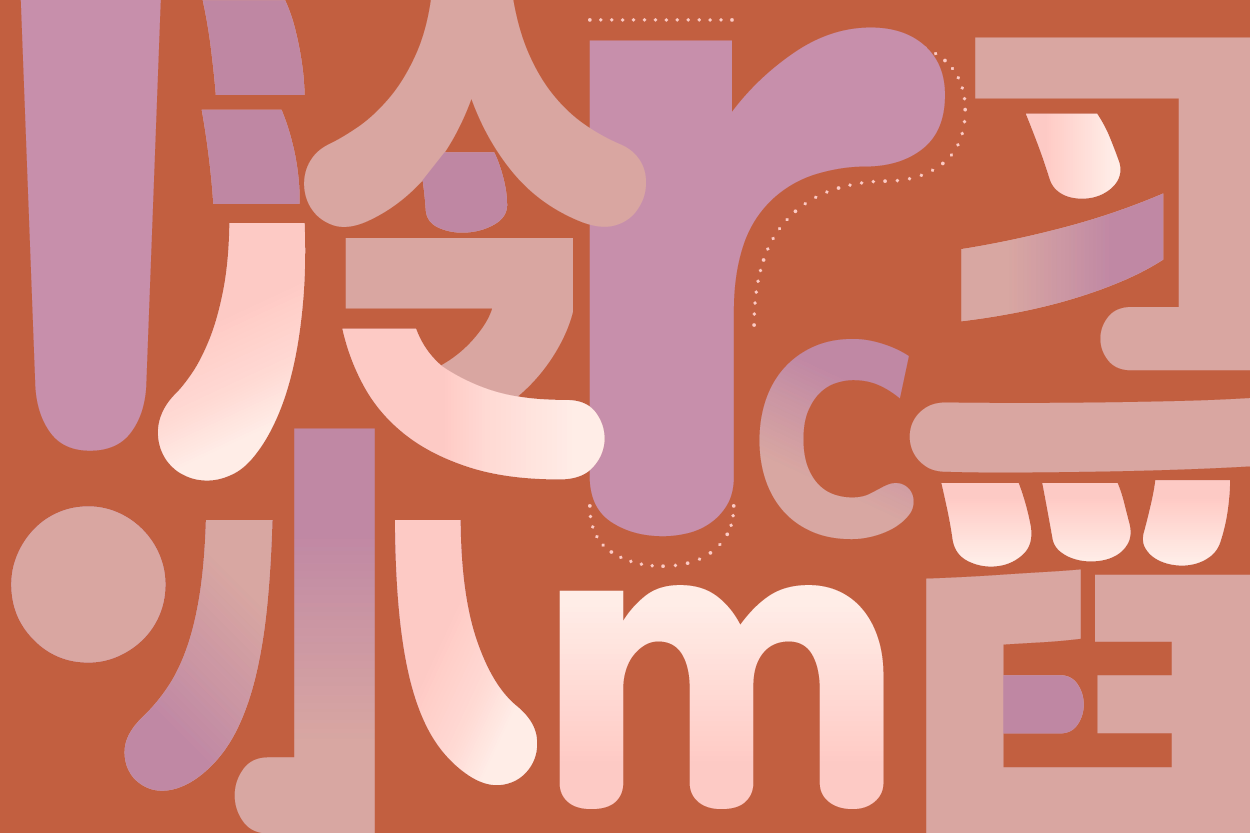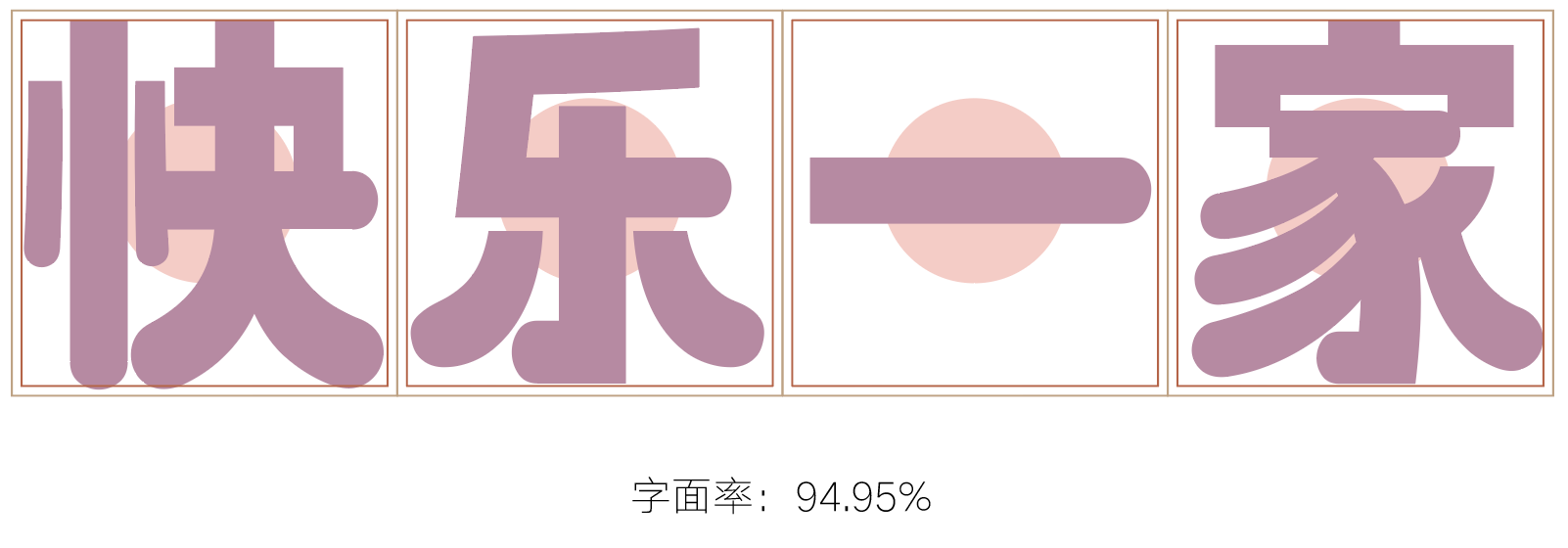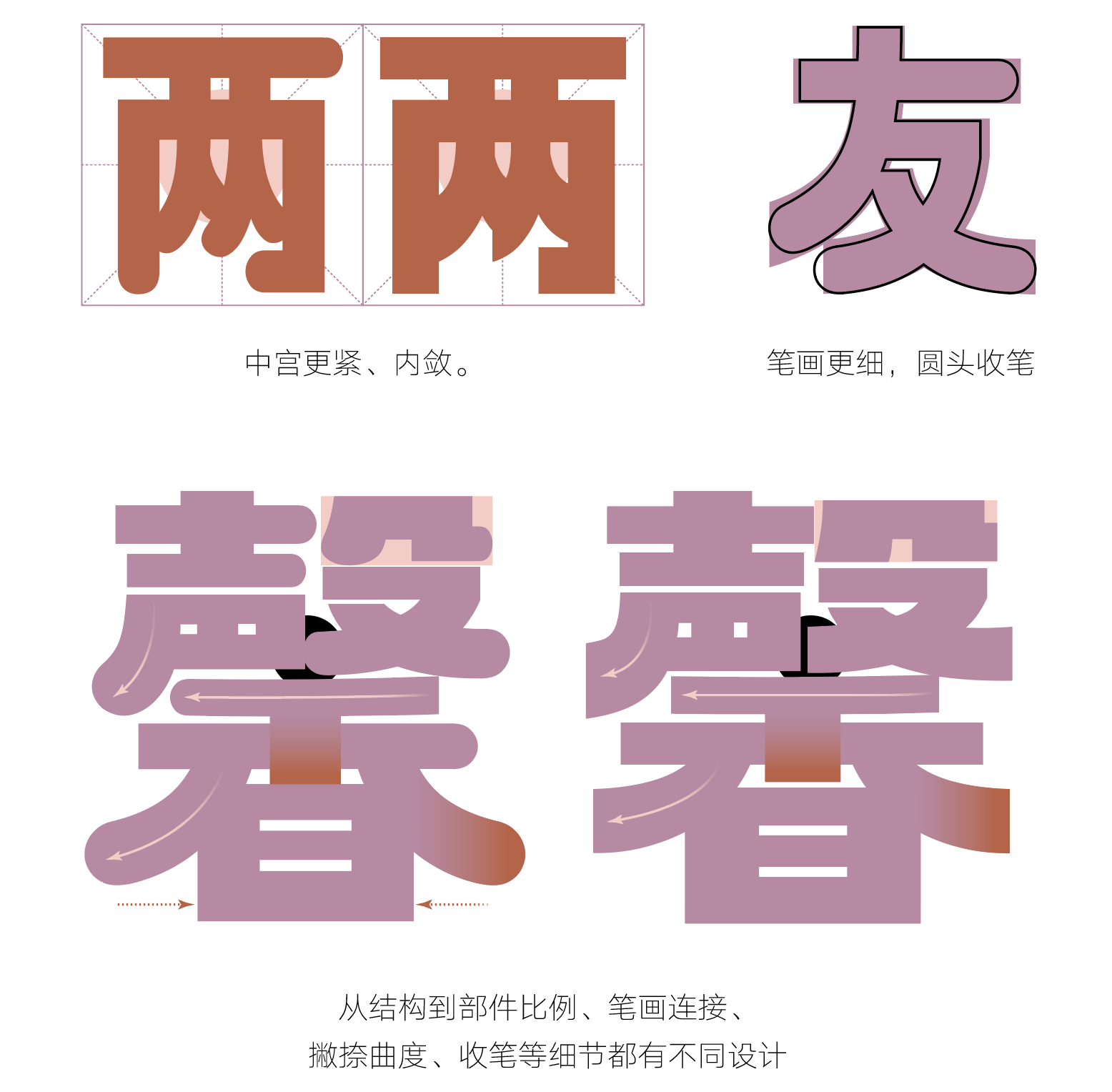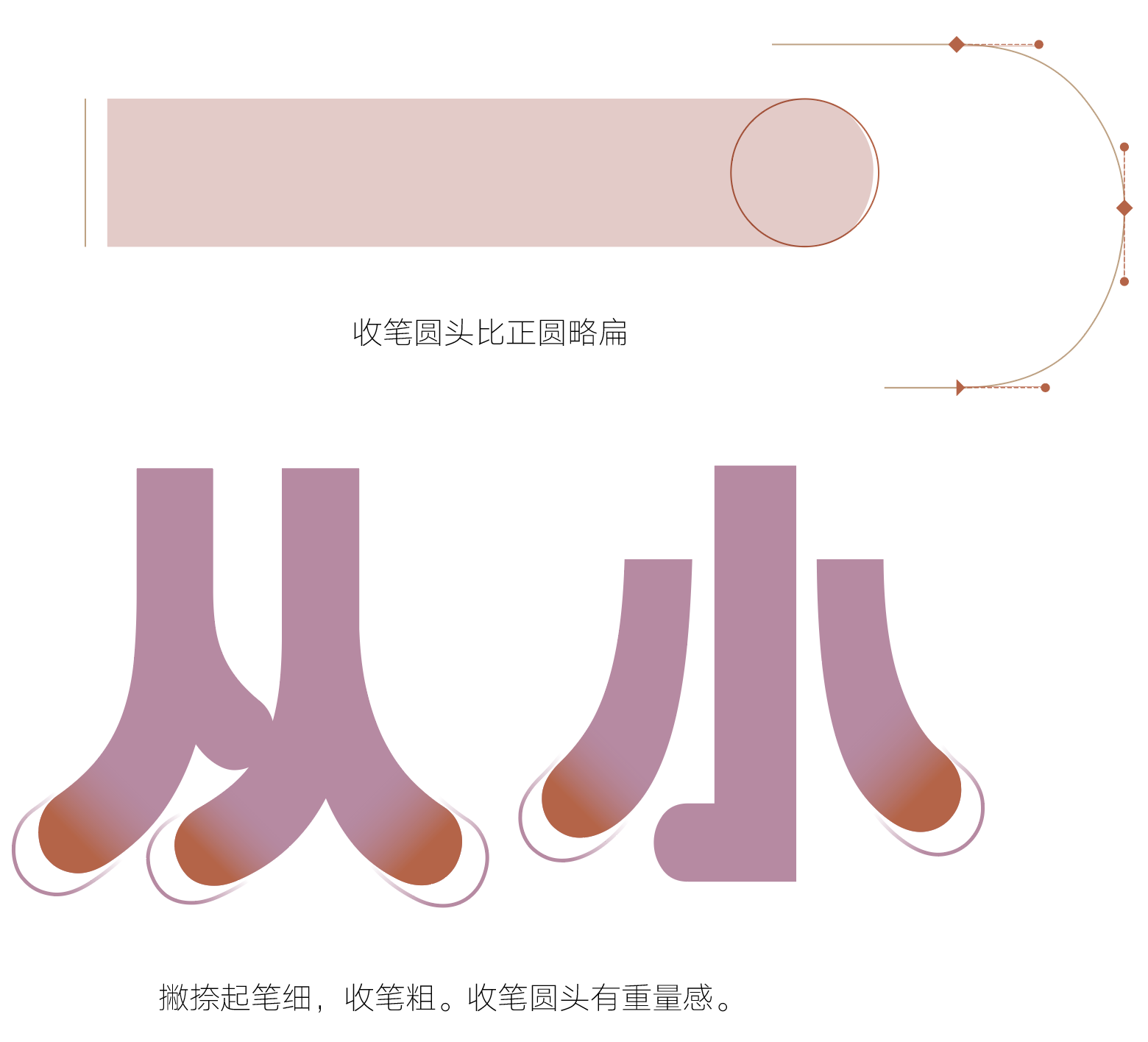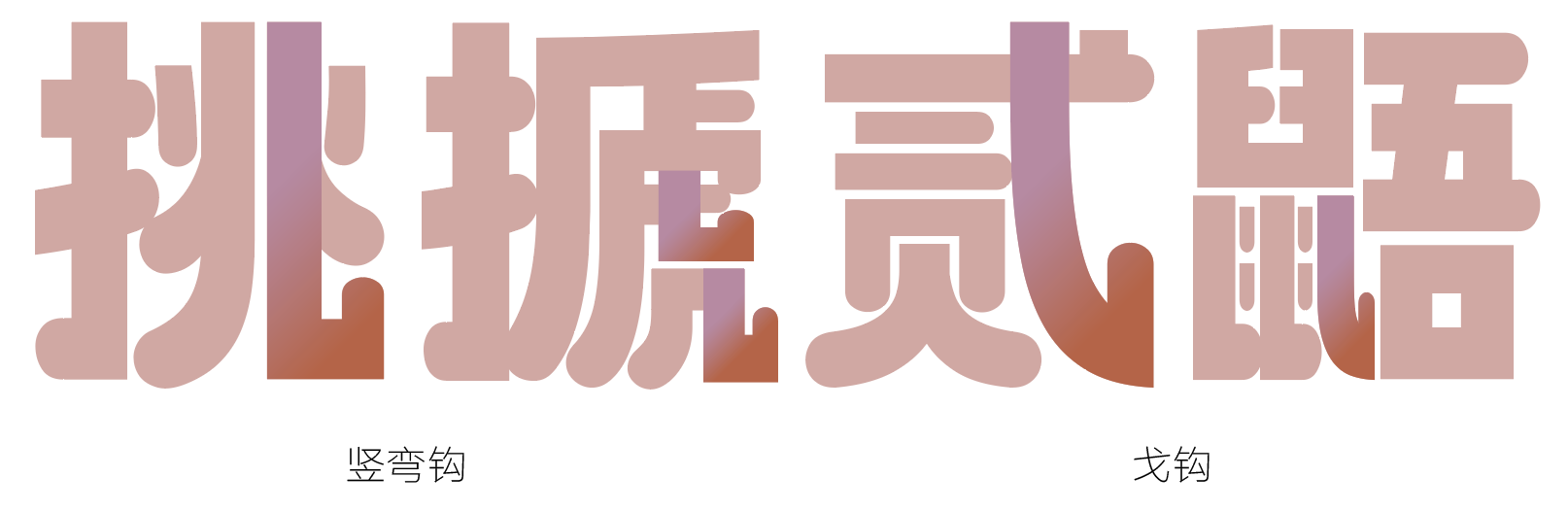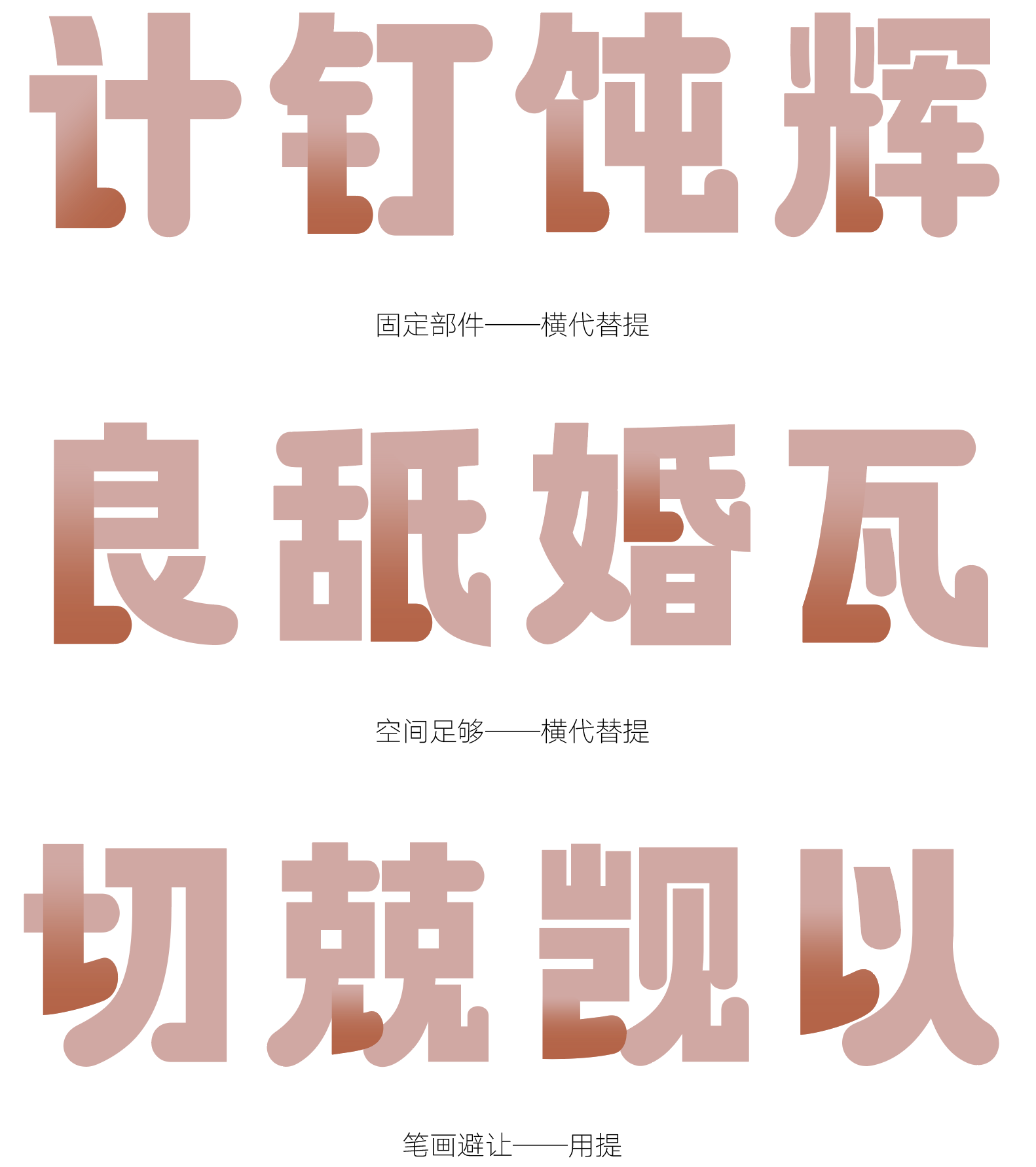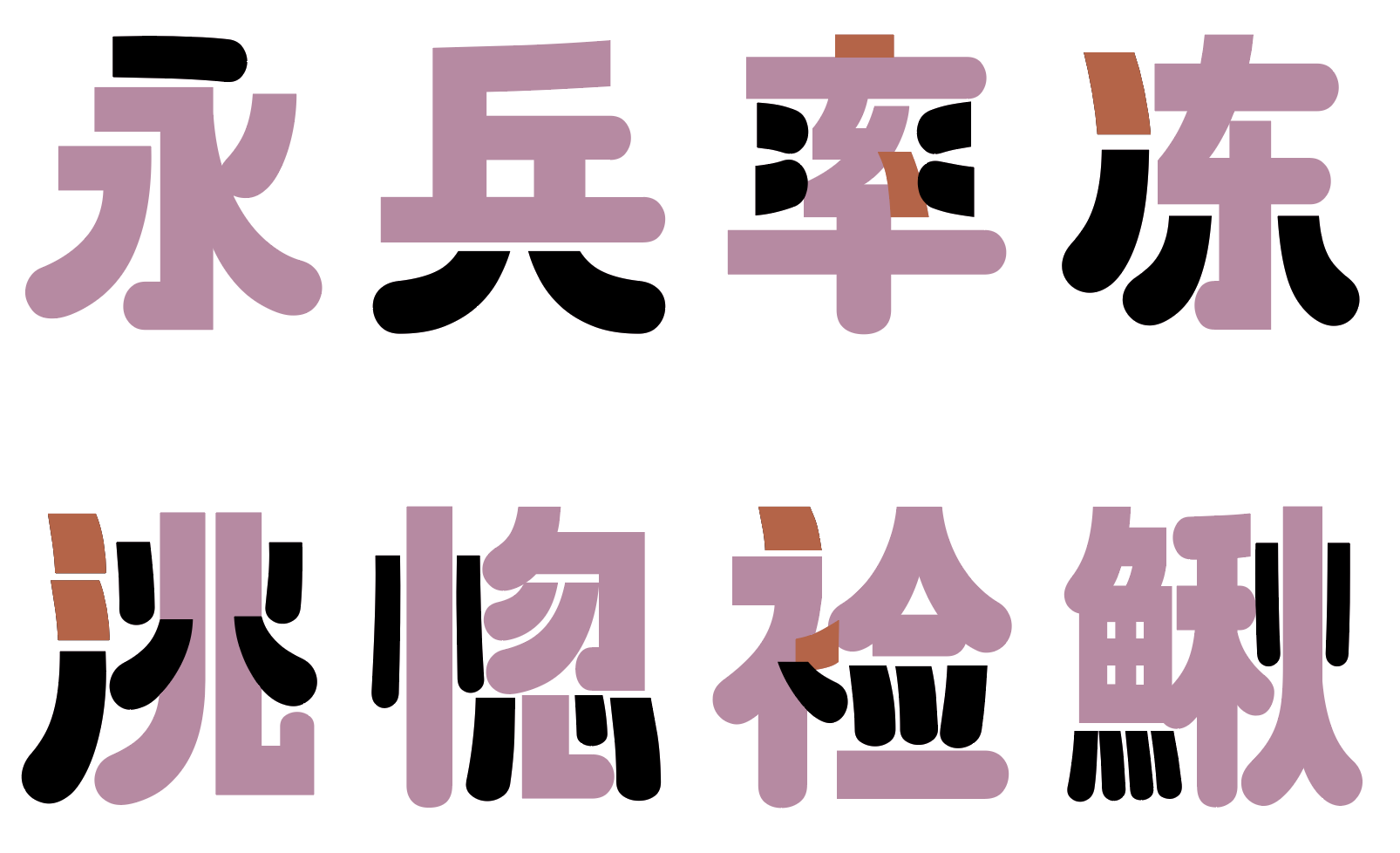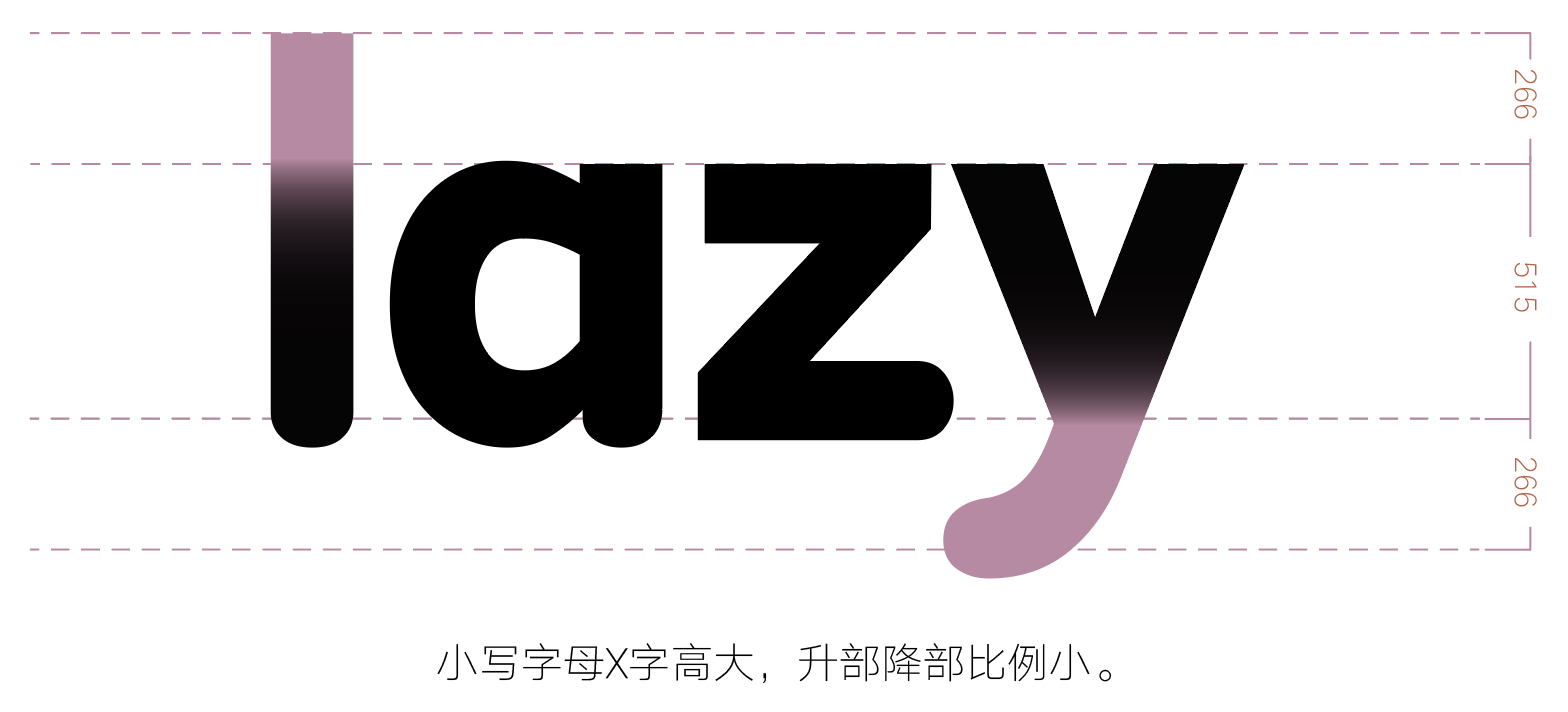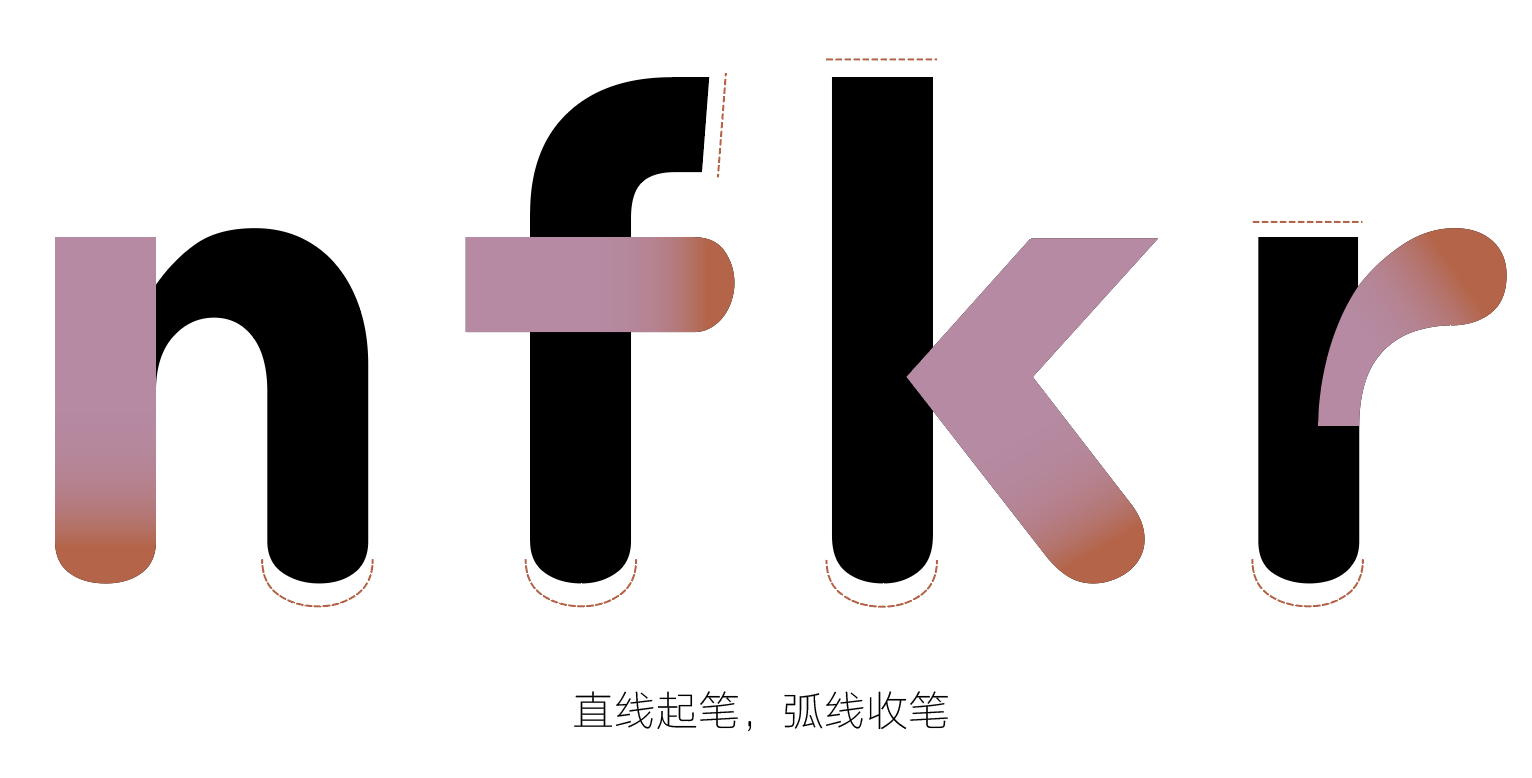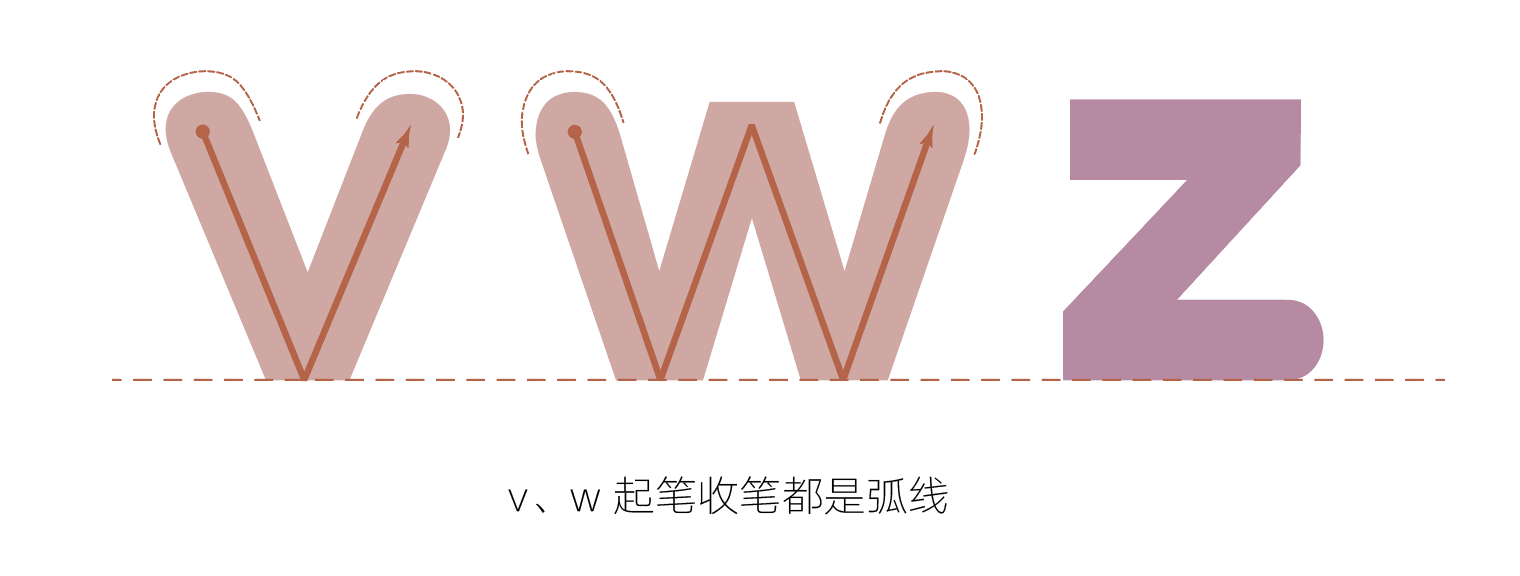
汉仪懒圆圆字体介绍,简洁有趣的标题字体
汉仪懒圆圆 | 整体特点
汉仪字库签约设计师顾正友设计了一系列简洁有趣的标题字。分别为汉仪懒黑黑、汉仪懒圆圆、汉仪懒酷酷和汉仪懒美美, “懒懒的一家”父母儿女的形象以不同字体风格跃然纸上。
“汉仪懒圆圆” 重心偏上。笔画收笔呈圆弧形,这种特点增加了字体的可爱程度,使字体更具亲和力。从视觉上诠释了“母亲”这一角色。可广泛应用在具有现代感的包装、品牌和电商设计等方面。
汉仪懒圆圆 | 字形特点
“汉仪懒圆圆”的字形略长,字面大,重心偏高,中宫收紧,撇捺饱满舒展。
与汉仪懒黑黑对比:
汉仪懒圆圆 | 笔画特点
“汉仪懒圆圆”的横平竖直,折笔为简洁明了的直角。横画比竖画稍细。笔画起笔为平行或垂直的整齐的切面,收笔为圆弧形。
仔细区分处理每个竖弯钩、戈钩。
竖提的细节处理:固定部件、空间足够时,用横代替竖提中的提;竖提在需要兼顾避让关系时使用提。
点画直线起笔,弧线收笔,造型丰富,灵活生动。大小、粗细、方向、曲度各不相同。只在部分固定部件和空间极小的地方,采用起笔收笔都是直线的点。
汉仪懒圆圆 | 中西文匹配
“汉仪懒圆圆”的西文为粗壮的无衬线字体。横平竖直,横细竖粗。绝大多数笔画都是直线起笔,弧线收笔,在稳重现代的风格上更显柔和,亲和力强。 与中文设计风格一致,搭配和谐。
小写字母只有“V W Z”底部是直线处理。
“汉仪懒圆圆”的大写字母宽度比例调整的更均衡。与图拉真大写字母相比较为明显,字母宽度比例大的“O M”设计的略窄,“H”调整的比“O”的2/3 略宽,“B”这类宽度小的字母加宽幅度大。 整组大写字母宽度比例变小,更有现代感。
汉仪懒圆圆 | 排版效果
汉仪懒圆圆 | 字体样张